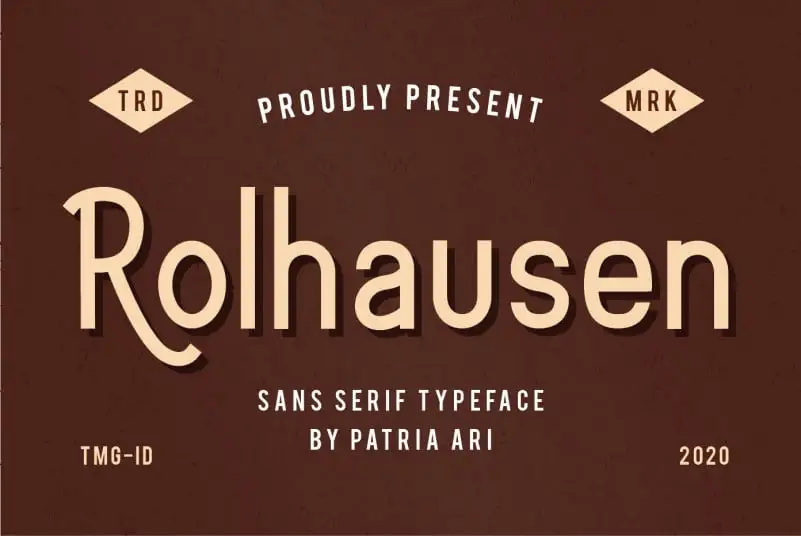
A Rolhausen Sans Serif Font é uma tipografia aberta perfeita para quem busca um visual clean e moderno para projetos visuais variados. Suave ao olhar, ela se destaca especialmente como a escolha ideal para logotipos de marca, rótulos de produtos, invitations e materiais de marketing. Além disso, sua simplicidade permite quebrar textos complexos em uma linha mais direta e elegante, tornando-a perfeita para headlines e banners. Ideal tanto para aplicativos quanto para impressão, a Rolhausen Sans Serif é uma ótima escolha para quem procura um look minimalista e moderno sem comprometer o impacto visual dos materiais de marketing. Aqui está uma tipografia que não apenas complementa sua necessidade específica de projeto gráfico, mas também ajuda você a criar designs incrivelmente sofisticados.